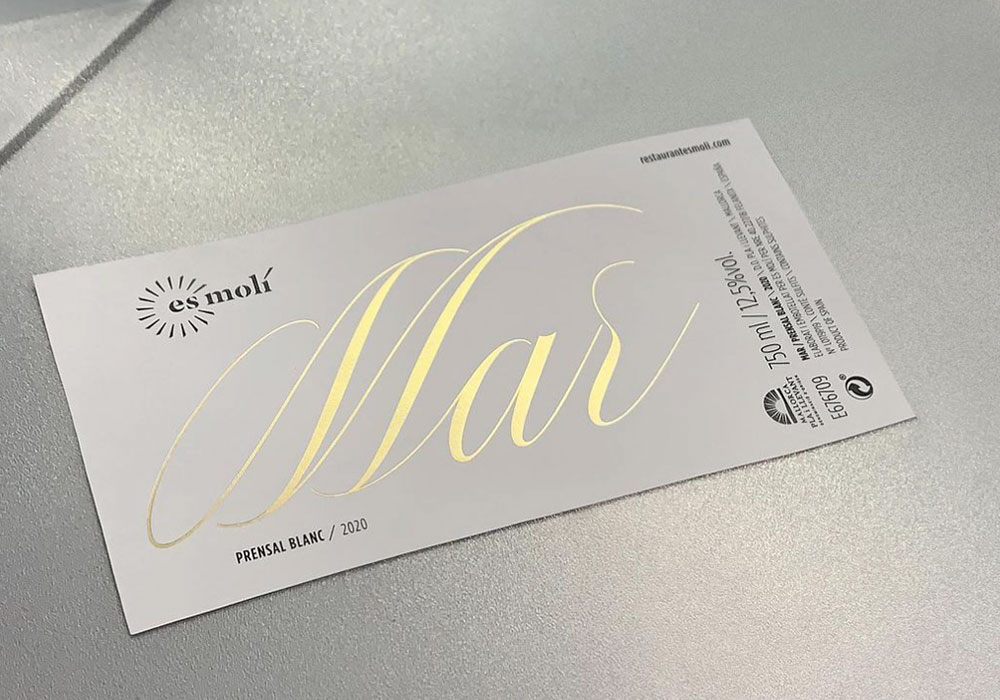
La tipografía caligráfica vuelve a estar de moda. Tras un tiempo en el que su presencia ha sido significativa, quizá este 2022 sea el año de la consolidación de su regreso.
La tipografía y el diseño gráfico son el reflejo, la consecuencia y, también, la respuesta a lo que sucede en la sociedad que las usa. El mundo es diverso, múltiple y contradictorio, y en tiempos de diversidad, donde los referentes y centros de gravedad son múltiples y en ocasiones contradictorios, el panorama tipográfico está conformado por las más variadas tendencias que conviven y se relacionan entre sí.
Las tensiones sociales derivadas de la diversidad son, paradójicamente, una vigorosa fuente de inspiración gráfica. En tipografía, la conjunción de contrarios genera riqueza visual. Si echamos un vistazo a las tendencias de la tipografía y el diseño gráfico que se vislumbran para este 2022 recién estrenado, se despliega ante nosotras un panorama abigarrado y multicolor.
Pero en prácticamente todas ellas aparece una misma palabra: nostalgia.
Infinidad de personas están convencidas de que el tipo de vida anterior a 2020 ya no va a volver y sienten la necesidad de recordar las cosas que les hacían felices entonces. Lo puramente humano se erige como la urgente reacción frente a inquietantes metaversos que prometen unir a las personas, pero que olvidan algo fundamental: el cuerpo.
¿Y qué hay más humano que la letra manuscrita?
No sabemos si por influencia directa de esta época convulsa, pero el caso es que las tipografías caligráficas están en alza desde hace tiempo. Bien combinadas, generan contrastes de gran potencia visual, cuando lo manual entra en contacto directo con lo artificial.
Habrá quien piense, no sin razón, que nada puede superar en emoción y expresividad a la caligrafía o el lettering surgidos directamente de la mano humana, porque lo que nos atrae es su perfecta imperfección, el variado flujo del ductus personal e intransferible de quien escribe.
La tipografía es idealización de la escritura, un artificio donde tiende a desaparecer la huella manual en favor de la racionalización. Por lo tanto, una tipografía caligráfica surge de una esplendorosa paradoja.
Quizá sea esta la razón por la cual las tipografías que imitan a la caligrafía del siglo XVIII o a la caligrafía inglesa o cooperplate vuelven a aparecer y a ser protagonistas en multitud de diseños.
Una presencia que llevamos observando desde hace tiempo, que durante el pasado 2021 ha sido significativa y que pensamos que se va a consolidar en el presente año.
Con todo, resulta indiscutible que hay tipografías caligráficas que son capaces de transmitir una calidad manual irresistible.
Veamos algunas de ellas que nos pueden ayudar a comprender que, en ciertas ocasiones, la nostalgia por el tiempo pasado puede generar hermosos frutos cargados de presente.
nautica, de resistenza type foundry
Inspirada, según sus autores, en la caligrafía de los cuadernos de bitácora usados en los barcos del siglo XVIII, tiene un marcado carácter romántico y evoca cierta nostalgia serena y elegante. Sus minuciosos detalles y acabados conforman un conjunto de gran belleza clásica, que, sin embargo, usada con astucia puede generar un impacto rompedor, al igual que sucede con el resto de tipos que siguen.
bellisima script y poem script de sudtipos
Diseñadas ambas por Alejandro Paul, Bellisima Script parte de un modelo de caligrafía española del siglo XIX sacado de un ejemplar de la biblioteca del legendario tipógrafo Joan Trochut que su nieto Alex Trochut le mostró a Paul. Poem Script, por el contrario, evoca un estilo de escritura a pluma estadounidense de finales del siglo XIX.
En Bellisima Script, Paul busca la síntesis, alejándose de exuberancias, y consigue una tipo rotunda y delicada a la vez: rotunda por su estructura y delicada por la armonía de sus formas sinuosas. A su vez, en Poem Script se deja patente el control y dominio de las habilidades manuales que se requerían hace siglos para crear unas letras tan ornamentales y exuberantes.
bickham script, de richard lipton para adobe originals
Inspirada en uno de los modelos más conocidos y usados de caligrafía inglesa, ahora, bien entrado el siglo XXI, vuelve con fuerza. Bickham Script debe su nombre al calígrafo y grabador George Bickham (1684–1758), autor de The Universal Penman, la serie de cuadernos de escritura más popular de su época.
Su autor, Richard Lipton, es un calígrafo y diseñador tipográfico neoyorquino, creador de gran número de fuentes tipográficas digitales, entre las que se cuentan excelentes tipos caligráficas como Sloop Script Pro o Savanna, además de la mencionada Bickhman.
itc edwardian script, de edward benguiat
Otro buen ejemplo de una tipo caligráfica inspirada en el estilo caligráfico inglés copperplate. ITC Edwardian Script, diseñada por el neoyorquino Edward Benguiat, busca sugerir, más que reproducir, el gesto apasionado de la escritura manual.
No podemos cerrar esta pequeña selección sin mencionar, aunque sea brevemente, Carta Nueva, la elegantísima tipo caligráfica diseñada por My-Lang Toung para Sharp Type a la que dedicamos una reseña hace unos meses.